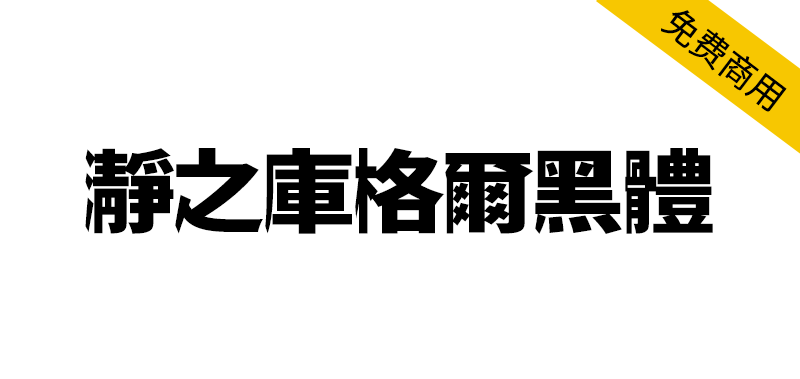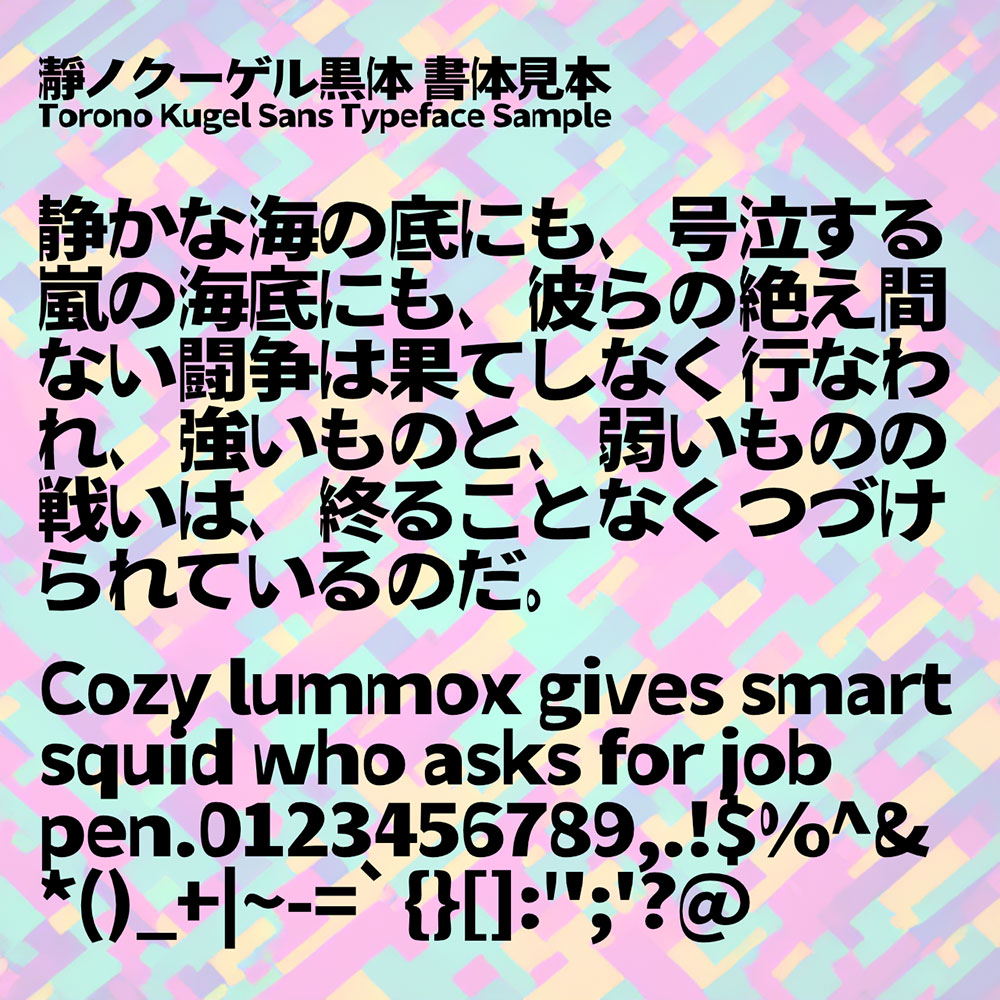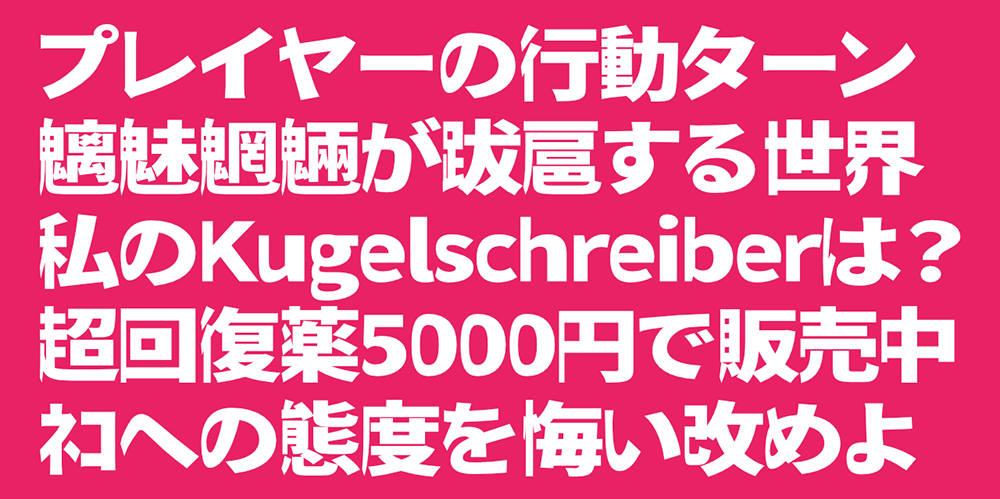
【瀞之库格尔黑体】基于思源黑体对文字右侧进行膨胀化处理
当传统字体追求对称平衡时,瀞之库格尔黑体却大胆打破常规,对文字右侧进行膨胀化处理,形成独特的左扁右宽视觉效果。这款基于思源黑体的开源字体,汲取日本设计灵感,为创作者提供了可自由商用的全新表达工具。
【瀞之库格尔黑体】基于思源黑体对文字右侧进行膨胀化处理
瀞之库格尔黑体(瀞ノクーゲル黒体)基于思源黑体修改而成,对文字右侧进行了膨胀化处理,形成左扁右宽的视觉效果,其设计灵感源自Fontworks公司的Rounded(ロウディ)字体。瀞之库格尔黑体(瀞ノクーゲル黒体)遵循SIL OPEN FONT LICENSE 1.1开源字体授权协议,允许商用、自由再分发及修改。